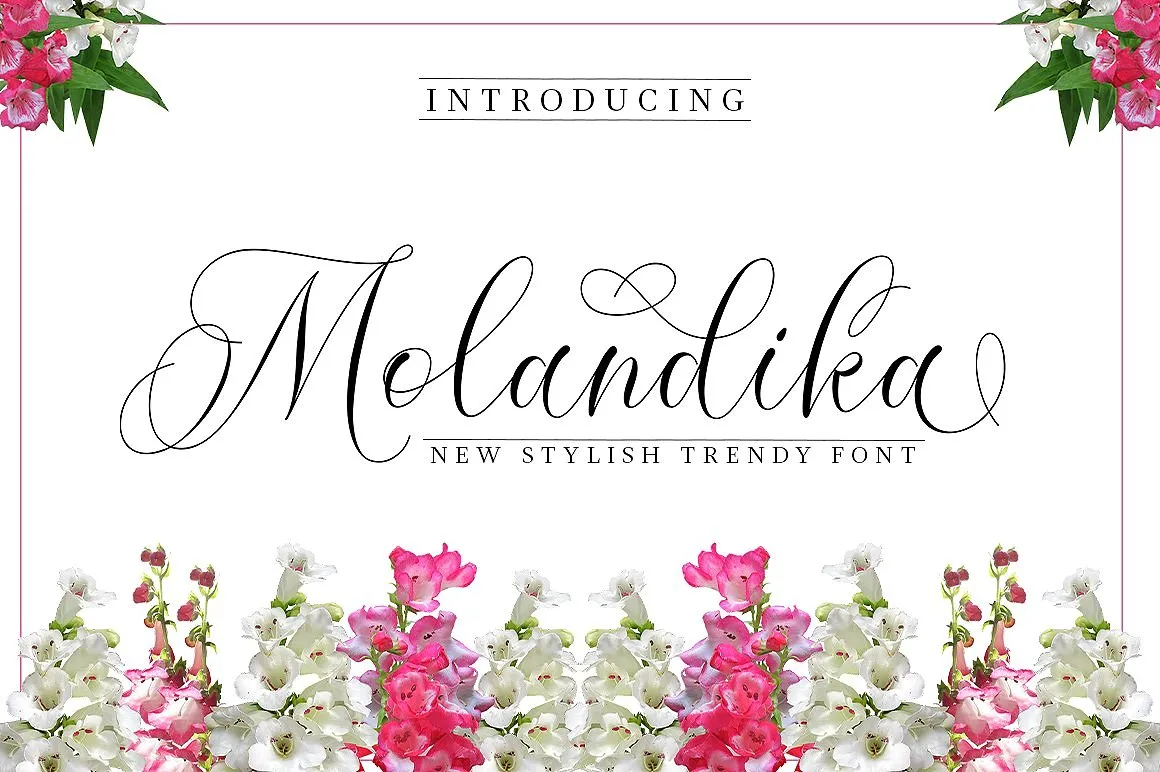
Molandika Calligraphy Font – Download Grátis
A novidade aqui é a Molandika Calligraphy Font, uma elegante fonte script que combina estilo com sofisticação. Desenvolvida pela Great Studio, Molandika Script oferece um toque feminino e amigável para projetos de diversos tipos. Suas linhas finas e desenhadas cuidadosamente permitem um design casual e poético, especialmente útil para aplicativos como identidades logomarciais, embalagens de produtos, convites casamentos, marcas de marca, headlines, sinalização, selos, assinaturas, capas de livros, posters, citações e muito mais. Não perca tempo, Molandika Font é a escolha ideal para aqueles que buscam uma fonte tanto sofisticada quanto versátil. Descubra hoje mesmo como essa elegante font pode transformar seus projetos digitais.